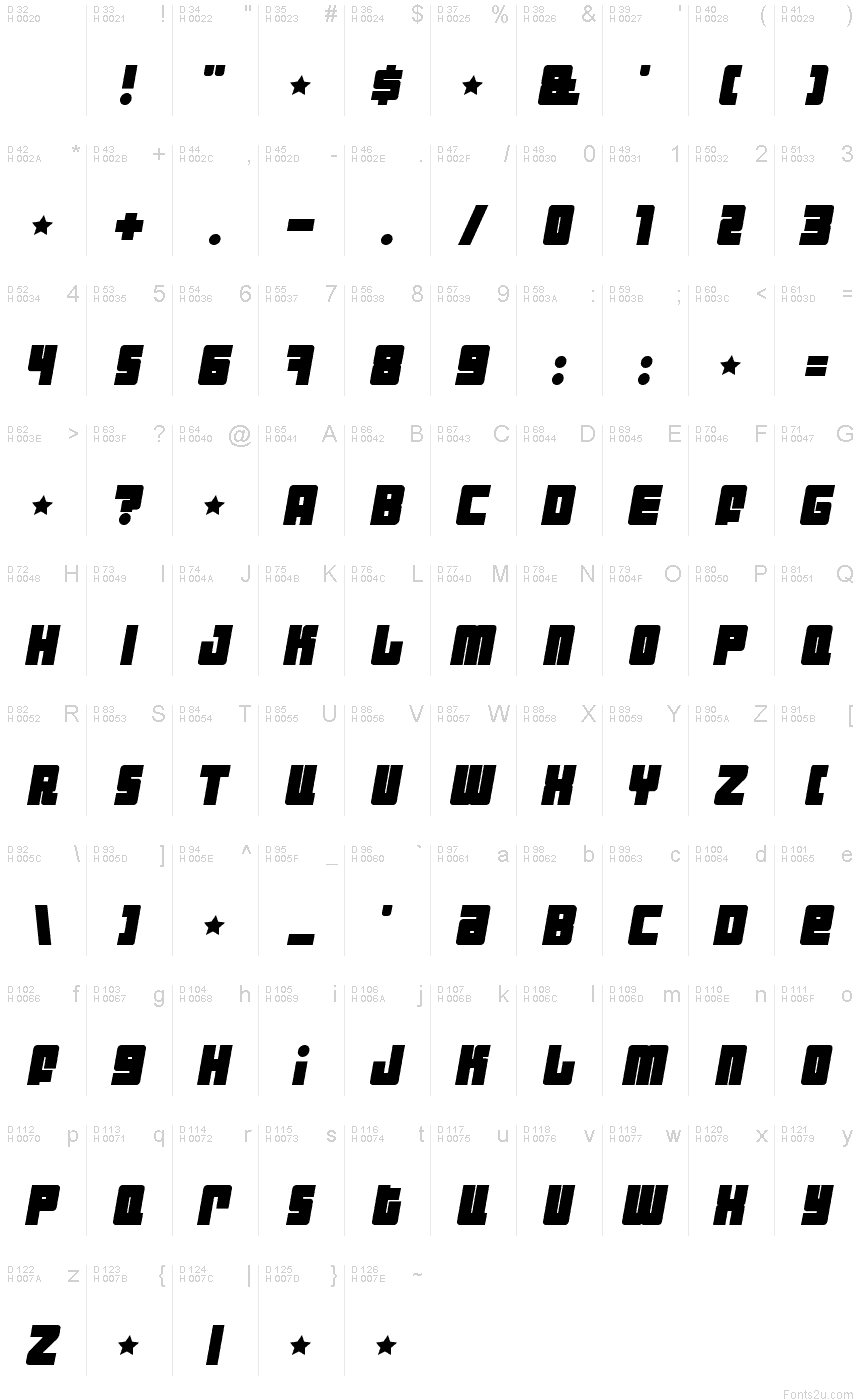
Industrial Decapitalist BoldItalic
Industrial Decapitalist Bold Italic od Dustbust Fonts to darmowy techniczny krój displayowy, który wygląda, jakby został wybity w stali przy dużej prędkości. Ciężkie, skompresowane litery pochylają się do przodu pod ostrym, aerodynamicznym kątem, nadając każdemu słowu poczucie ruchu i mechanicznego napięcia. Solidne czarne kształty wydają się masywne i industrialne, ale dzięki nachyleniu nigdy nie wyglądają statycznie ani sztywno.
Dzięki Industrial Decapitalist Bold Italic Twoje nagłówki idealnie wpasują się w logotypy e-sportowe, plakaty wyścigowe, okładki książek sci-fi, industrialny branding, grafikę eventów technologicznych czy odważne miniatury na YouTube. Ścisły rytm liter tworzy mocny blok koloru, dlatego ten darmowy font świetnie sprawdza się w krótkich hasłach ustawionych w bardzo dużym rozmiarze. Połącz go z czystym geometrycznym krojem bezszeryfowym w lżejszej odmianie dla tekstu głównego, aby zachować agresywny, ale czytelny wygląd.